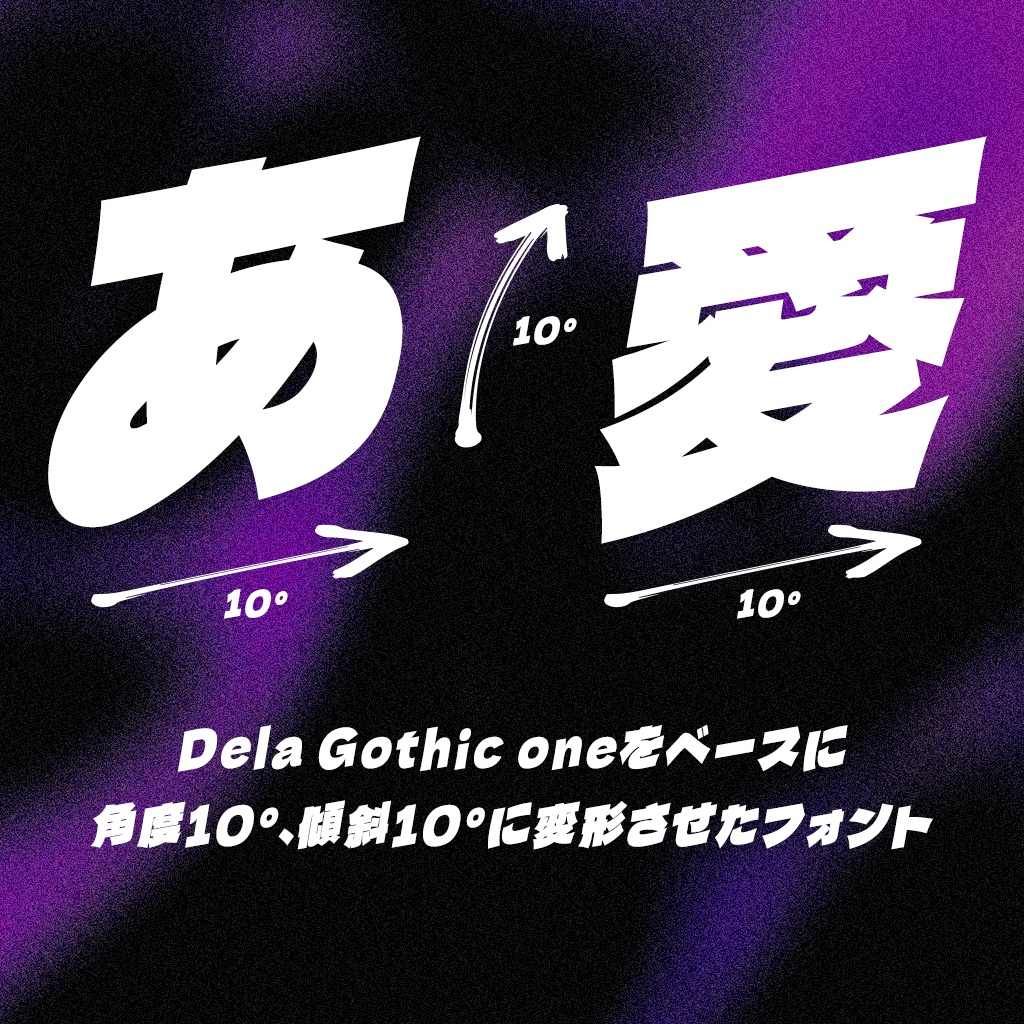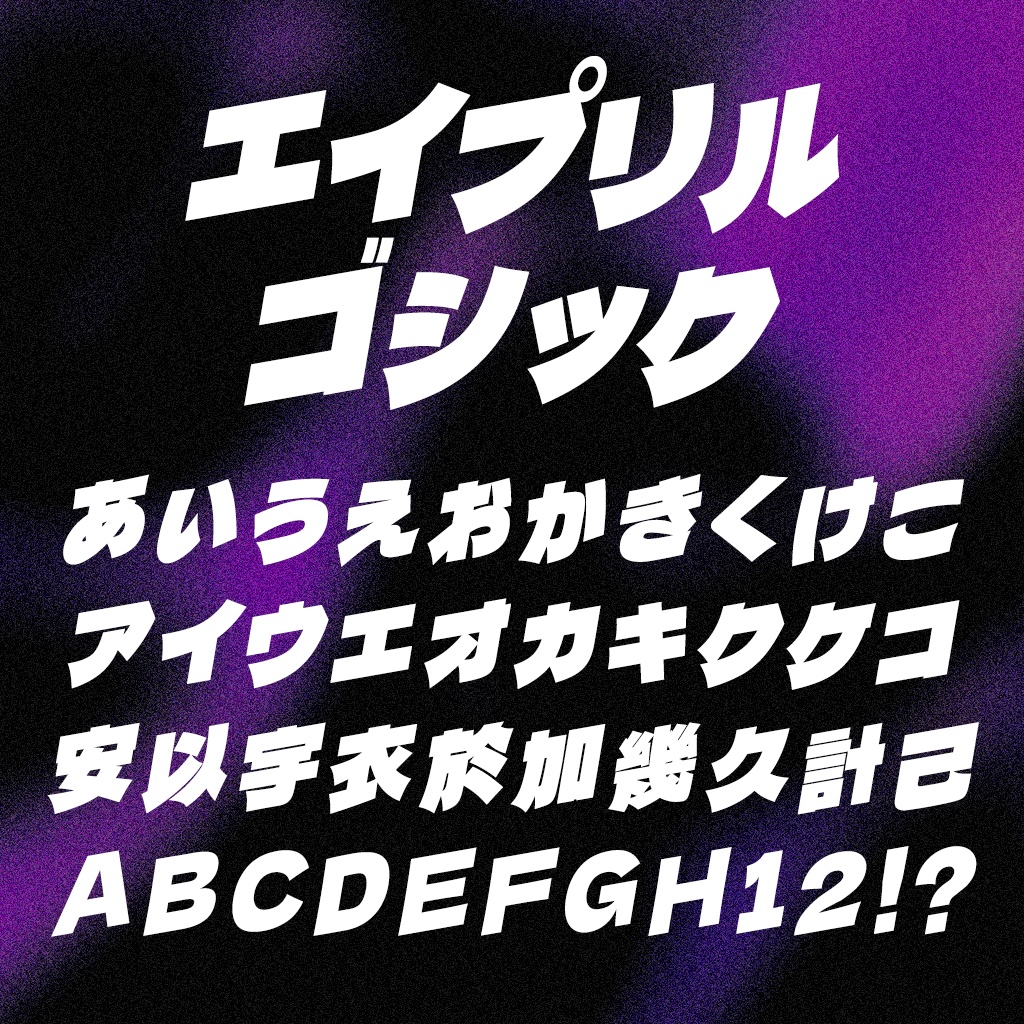
エイプリルゴシック(フリーフォント)
【概要】 エイプリルゴシックは、デラゴシック(Dela Gothic One)を改変したフリーフォントです。 角度10°、傾斜10°に変形させたフォントです。カートゥーンのようなコミカル感やスピード感・躍動感を表現したい見出しにおすすめです。 無料版と投げ銭版(¥500)のフォント内容は同一です。 【ライセンス・規約について】 このフォントはSIL Open Font License 1.1で公開されています。 個人・商用にかかわらず無償で使用可能で、ゲーム等への組み込みも可能です。 詳しいSILライセンスについてはサイトをご確認ください。 https://licenses.opensource.jp/OFL-1.1/OFL-1.1.html 当フォントを利用して発生した、いかなる損害についても作者は責任を負いません。 フォントデータをダウンロードした時点で利用規約に同意したものとみなします。 【改変元フォント】 デラゴシック(Dela Gothic One) 関係者に深くお礼申し上げます。 【アップデート】 2026/05/13《ver1.01》一部文字のバグを修正しました